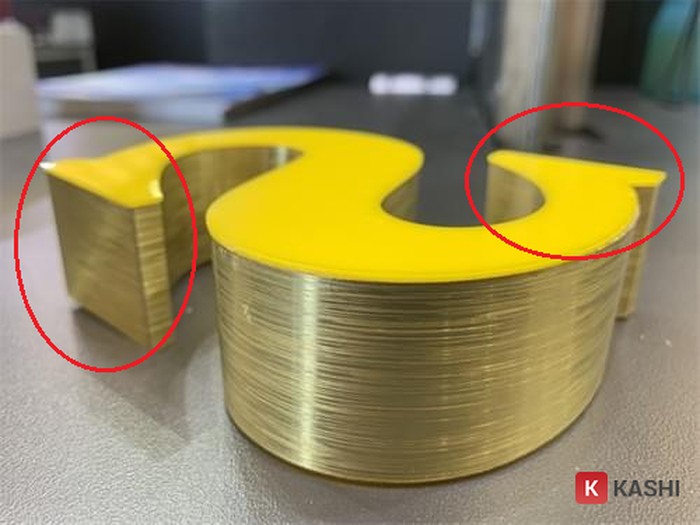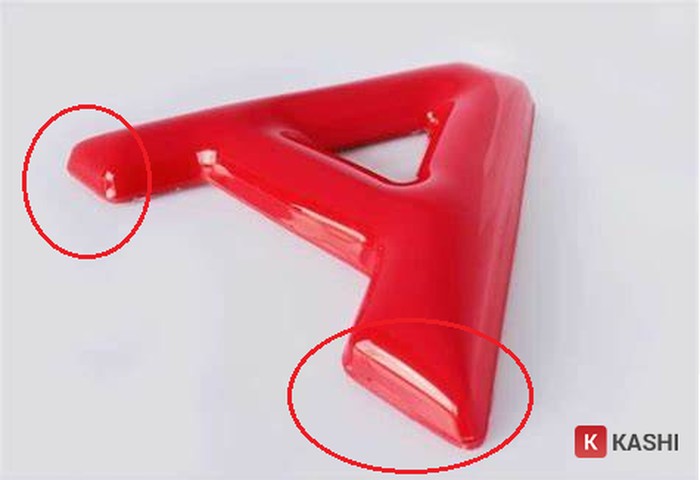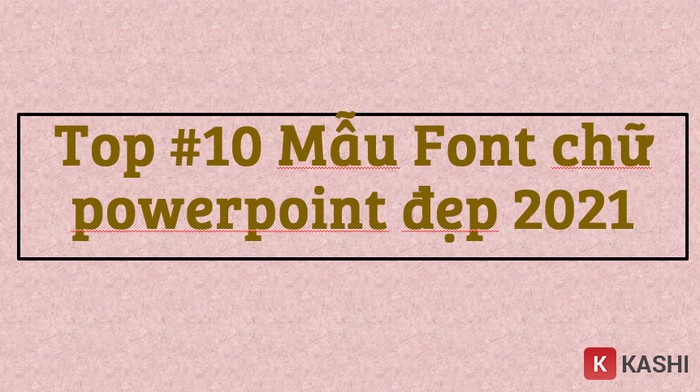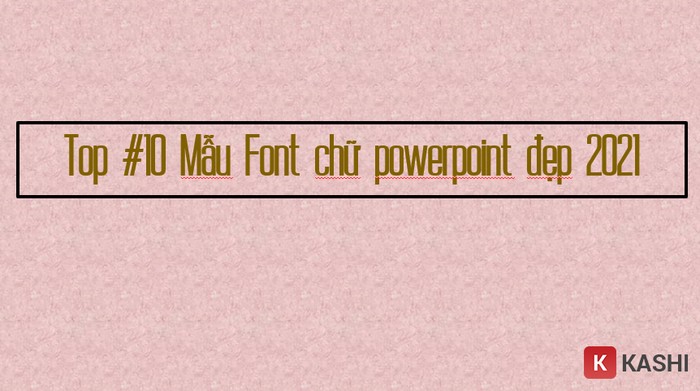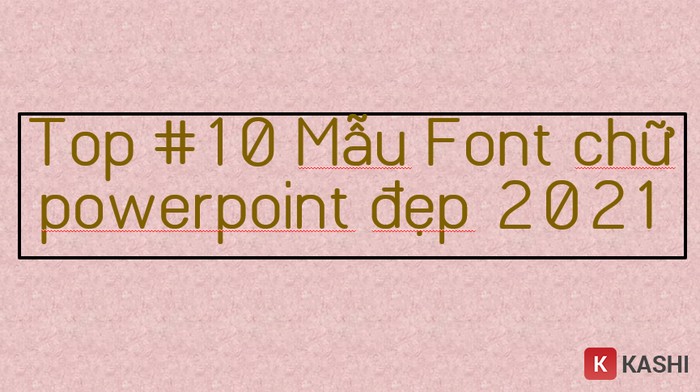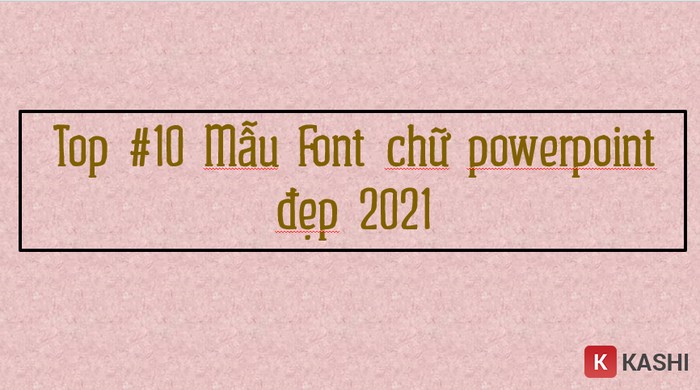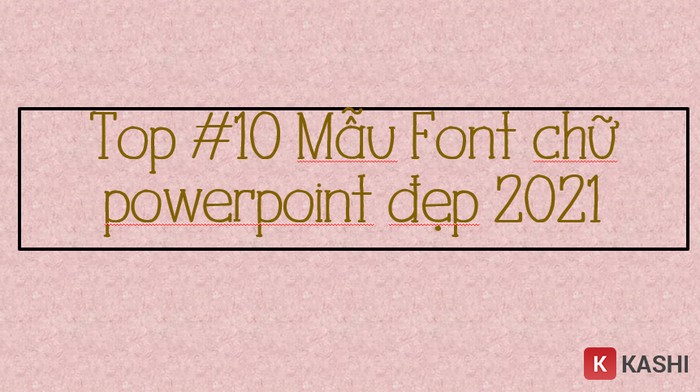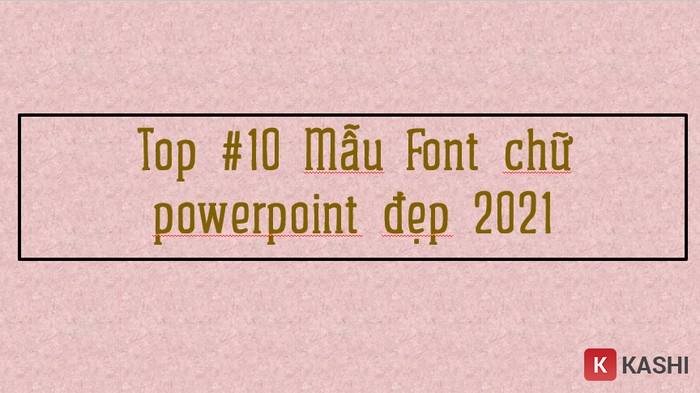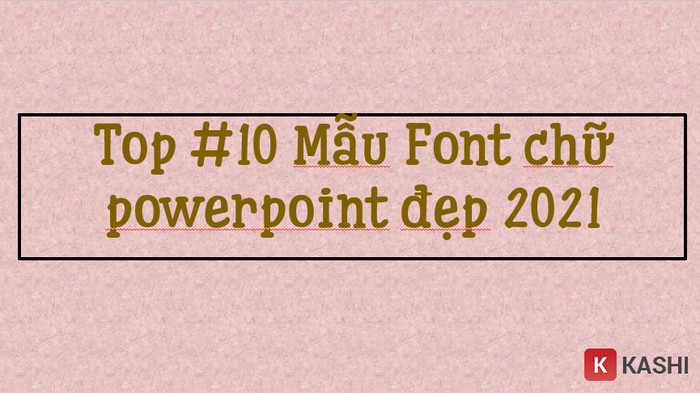
Top 10 Font Chữ PowerPoint Đẹp và Chuyên Nghiệp Nhất 2025
Bạn đang tìm kiếm font chữ PowerPoint đẹp và phù hợp cho bài thuyết trình? Font chữ đóng vai trò quan trọng trong việc truyền tải thông tin và tạo ấn tượng với người xem. Dù PowerPoint cung cấp một số font chữ mặc định, nhưng để tạo sự khác biệt và chuyên nghiệp, bạn cần khám phá thêm nhiều lựa chọn khác. Bài viết này sẽ giới thiệu 10 font chữ PowerPoint đẹp nhất 2025 và các nguồn tài nguyên hữu ích khác.
Tổng hợp các font chữ PowerPoint đẹp
Font Chữ PowerPoint Đẹp là gì?
Font chữ PowerPoint đẹp là những font chữ thu hút, dễ đọc và phù hợp với nội dung bài thuyết trình. Việc lựa chọn font chữ phù hợp giúp nâng cao tính thẩm mỹ và hiệu quả truyền tải thông tin.
Các font chữ PowerPoint đẹp mắt
Tuy nhiên, việc tìm kiếm font chữ phù hợp không phải lúc nào cũng dễ dàng. Bài viết này sẽ giúp bạn khám phá những font chữ độc đáo và chuyên nghiệp, từ đó tạo nên những bài thuyết trình ấn tượng.
Font chữ ảnh hưởng lớn đến thiết kế tổng thể của bài thuyết trình. Một font chữ không phù hợp có thể làm giảm hiệu quả của hình ảnh, hiệu ứng và bố cục. Vì vậy, hãy lựa chọn font chữ cẩn thận để phù hợp với phong cách và thông điệp bạn muốn truyền tải.
Phân Loại Font Chữ Thường Dùng trong PowerPoint
Có rất nhiều font chữ khác nhau, nhưng hầu hết chúng đều thuộc hai loại chính: Serif (chữ có chân) và Sans Serif (chữ không chân).
Sans Serif: Loại font chữ này mang đến vẻ hiện đại, gọn gàng và dễ đọc. Chúng thường được sử dụng cho nội dung chính của bài thuyết trình.
Ví dụ về font chữ không chân
Serif: Font chữ Serif có các nét chân, tạo cảm giác cổ điển, trang trọng và thường được sử dụng cho tiêu đề hoặc các đoạn văn bản ngắn.
Ví dụ về font chữ có chân
Top 10 Font Chữ Tiếng Việt Đẹp cho PowerPoint 2025
1. iCiel Altus Serif
iCiel Altus Serif là font chữ mang phong cách cổ điển, độc đáo với các nét viết nguệch ngoạc, tạo điểm nhấn cho bài thuyết trình.
Font iCiel Altus Serif
2. iCielmijas-ultra
Với nét chữ tròn trịa, rõ ràng, iCielmijas-ultra mang đến vẻ đẹp nghệ thuật, nhẹ nhàng và dễ đọc.
Font iCielmijas-ultra
3. UVF – Kizo
UVF – Kizo là lựa chọn hoàn hảo cho những ai yêu thích sự tối giản. Font chữ nhỏ gọn, giúp nội dung bài thuyết trình trở nên súc tích hơn.
Font UVF - KizoFont UVF – Kizo
4. UVFLHLine1SansThin
UVFLHLine1SansThin có nét chữ khỏe khoắn, thể hiện sự hoàn hảo trong phong cách và khoảng cách chữ viết.
Font UVFLHLine1SansThin
5. iCielzitronefy
iCielzitronefy mang nét chữ mềm mại, tạo cảm giác hài hòa và lãng mạn cho bài thuyết trình.
Font iCielzitronefy
6. BreeSerif
BreeSerif là font chữ phổ biến với nét chữ đơn giản nhưng tinh tế, giúp tiêu đề trong bài thuyết trình trở nên nổi bật hơn.
Font BreeSerif
7. iCielCucho-bold